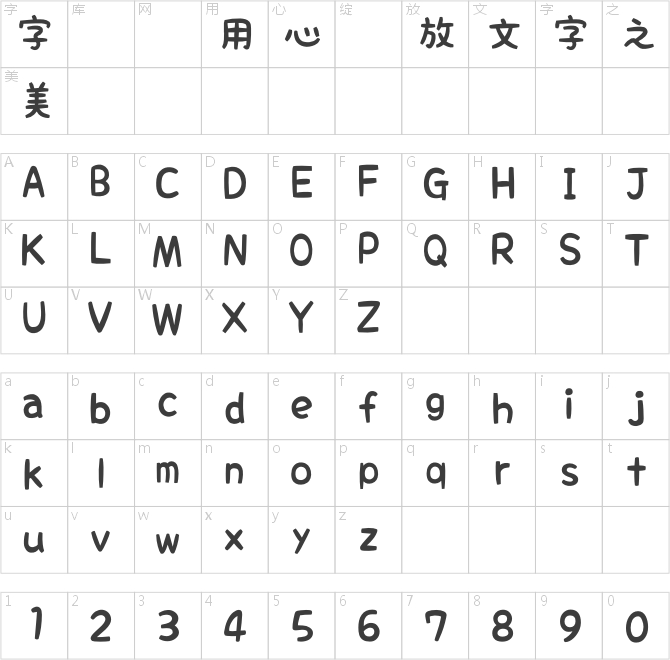
字体名称: KF手写体
字体类型: 日文字体
KF手写体
KF手写体介绍
「 KF手写体 」这款字体,虽然这款字体是日文字型,不过也有很多的汉字,日文字型越来越受大家的喜爱,我想应该就是有支持部分汉字的原因, 「 KF手写体 」这款是属于手写风格,整体的感觉相当相当的可爱,重点是这款字型除了个人免费使用之外,也可以商业使用。
KF手写体效果图